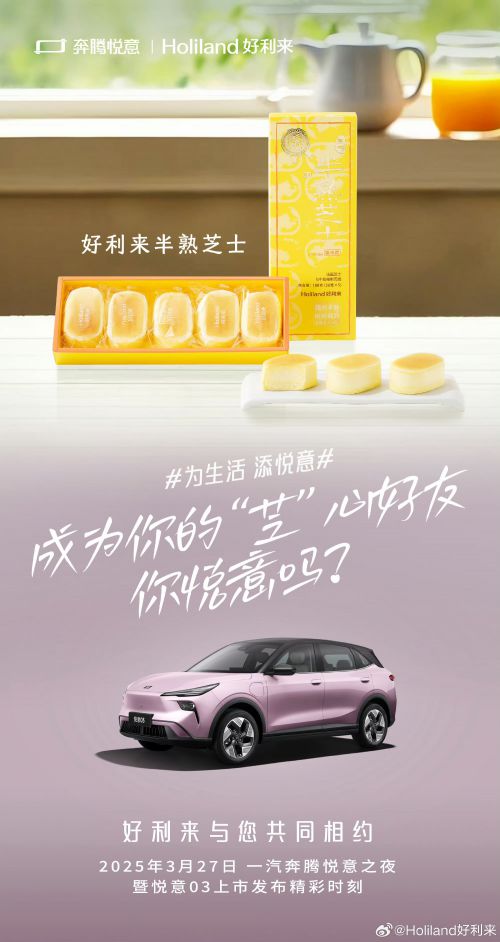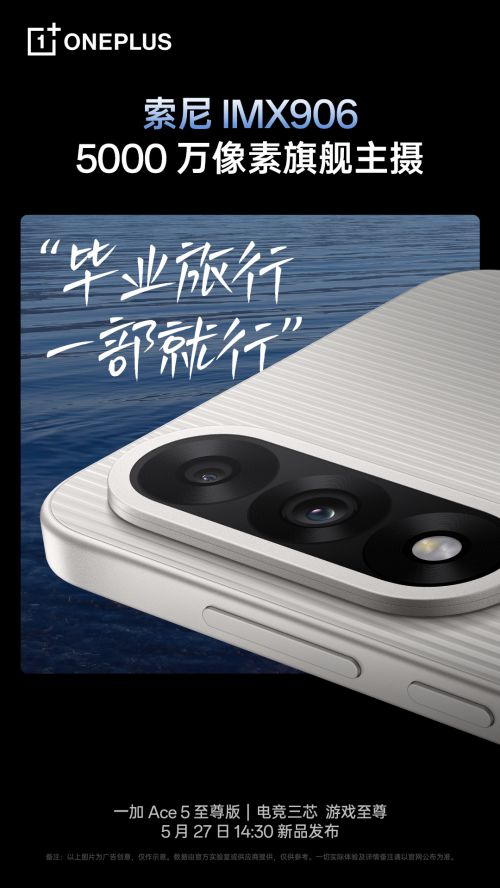
白路俏丽手写体
【白路俏丽手写体】是一款风格灵动的免费商用手写体字体,以其自然流畅的手写笔触著称,完美适配简体中文常规字符集需求。 白路俏丽手写体字形修长,重心居中,中宫设计适中,整体呈现出优雅的视觉效果。字体笔画整体偏细且粗细均匀,起笔收笔处的圆头设计增添了柔和质感,部分笔画自然的弧度与连笔处理,完美还原了手写书写的流畅连贯性与随性美感。 白路俏丽手写体适用于社交媒体配图、手账设计、邀请函、贺卡、个人博客等多种场景,能为作品注入温暖灵动的手写温度。其免费商用授权特性,结合清晰的常规字符集支持,让创作者无需担心版权问题,轻松实现设计创意。无论是日常文字排版还是个性化设计,白路俏丽手写体都能以其独特的手写魅力与实用属性,成为手写风格设计的理想选择。